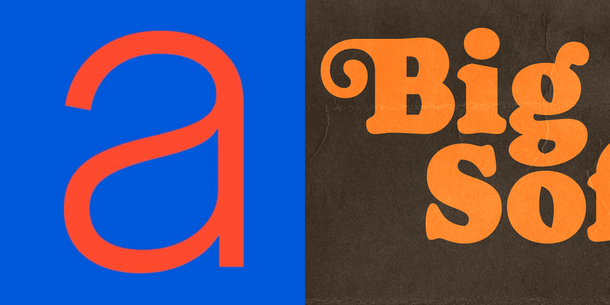
Monotype gewinnt die Schriftkataloge Milieu Grotesque und Paulo Goode für seine Produktfamilie.
Der Anbieter von Schrift und -Technologie Monotype stellt ab sofort fünf Premium-Schriftfamilien aus dem Katalog von Milieu Grotesque und dem aktuellen Schriftkatalog von Paulo Goode zur Verfügung.
Berlin / WOBURN, 14. März 2023. Das 2010 von den Grafikdesignern Timo Gaessner und Alexander Colby gegründete Unternehmen Milieu Grotesque wurde ursprünglich als Schriftplattform für Designer ins Leben gerufen. Unter der Leitung von Timo Gaessner und Maiko Gubler entwickelte sich das Unternehmen zu einer hoch angesehenen Foundry mit dem Ruf, langlebige und elegante Schriften zu entwickeln. Zu den fünf Schriftfamilien von Milieu Grotesque gehören: Maison Neue, eine Superfamilie mit 40 Schnitten als minimalistische Hommage an das moderne Design des frühen zwanzigsten Jahrhunderts. Boutique, eine anspruchsvolle serifenlose Schrift, die eine Hommage an das Didone-Skelett ist. Patron, eine serifenlose Schrift, die von zwei ungleichen Schriftdesignern, Günther Gerhard Lange und Roger Excoffon, beeinflusst wurde. Maison, eine einzeilige Grotesk, die mit starren Elementen konstruiert wurde, um ein minimalistisches industrielles Gefühl zu erzeugen und Chapeau, frei inspiriert von einem Brief von Johnny Cash, der auf einer alten IBM-Schreibmaschine geschrieben wurde.
Milieu Grotesque-Gründer Timo Gaessner: „Monotype ist das perfekte Zuhause für den Milieu Grotesque-Katalog und wir sind gespannt, was die ‚frischen Augen‘ des Monotype-Studios in Bezug auf technologische und gestalterische Entwicklungen für die Schriften bringen werden.“
Paulo Goode, der ursprünglich Grafik- und Website-Designer war, kam 2014 zum ersten Mal mit Schriftdesign in Berührung. Seitdem hat er einen reichhaltigen und vielfältigen Schriftkatalog erstellt, der sich hauptsächlich auf Branding-Anwendungen konzentriert. Paulos aktueller Katalog umfasst 42 Schriften, darunter: Audacious , eine selbstbewusste und schrullige Serifenschrif. Cream, eine weiche Serifenschrift, die von Oswald Bruce Coopers gleichnamiger Schrift inspiriert ist und Majesty, eine raffinierte, eingeschnittene Schrift, die von der jahrhundertealten Tradition der gravierten Schriften inspiriert ist.
Designer Paulo Goode: „Seit meinem Start in den Bereich Typografie im Jahr 2015 hat Monotype mein Talent gefördert und meine Arbeit aufgewertet. Obwohl ich eine Ein-Mann-Foundry bin, hat Monotype die Qualität und den Wert meiner Arbeit erkannt und meine Schriften 2020 in die Premium Collections aufgenommen. Dass Monotype nun mein Portfolio übernimmt, zieht eine positive Bilanz unter meine ersten sieben Jahre als Schriftdesigner. Und stellt sicher, dass meine Schriften ein dauerhaftes Zuhause haben und auch noch lange nach meinem Tod verfügbar sein werden.“
Der Paulo Goode-Schriftkatalog wird auch weiterhin über alle Plattformen von Monotype verfügbar sein. Die Milieu Grotesque-Schriften sind als Teil der Monotype Fonts plus-Sammlung über Monotype Fonts erhältlich. Hier stehen mehr als 40.000 Schriften, kombiniert mit dem Fachwissen der weltbekannten Schriftdesigner von Monotype und einer zuverlässigen, sicheren Schriftverwaltung zur Verfügung.
Monotype CEO Ninan Chacko: „Mit diesem Schritt sind die Schriften von Milieu Grotesque und Paulo Goode in eine der weltweit größten Schriftbibliotheken aufgenommen. Unter unserer Obhut werden diese erstklassigen Produkte nicht nur weltweit bekannt und stehen Tausenden von Kreativprofis zur Verfügung. Sie werden damit auch kontinuierlich aktualisiert, um die neuesten technologischen Fortschritte und typografischen Trends widerzuspiegeln. Somit ist sichergestellt, dass sie für viele Jahre relevant bleiben.“